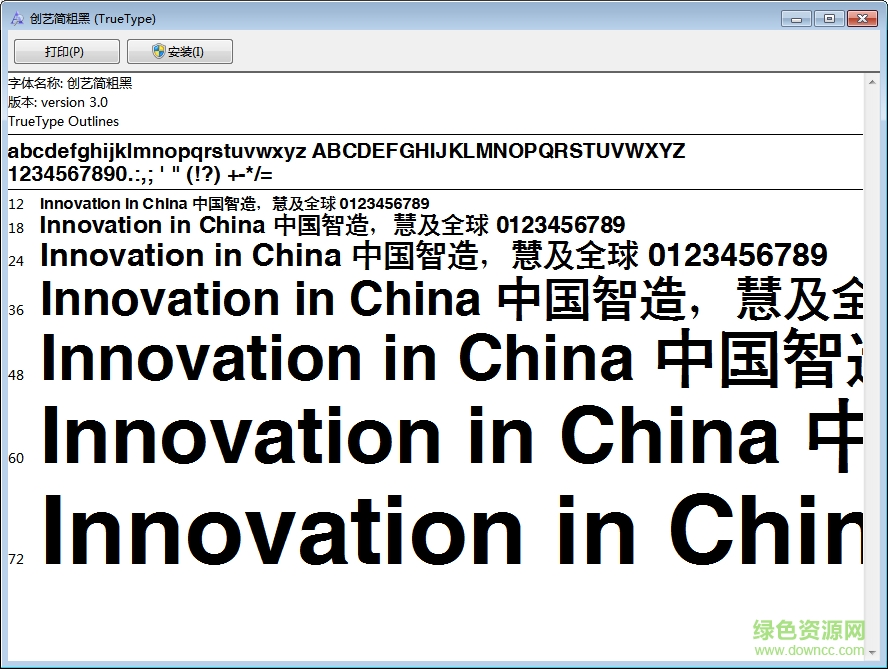
ctcuheisj
ctcuheisj 创艺简粗黑字体是一款线条粗壮的黑体字体,笔画整洁,字形饱满,轮廓清晰,常常用作各种文章的标题或标语,喜欢的朋友快来下载吧!
ctcuheisj字体特点
本款字体端正,大气、壁画横平竖直,笔迹全部一样粗细,整体效果十分不错,适用于文字排版、印刷等方面
ctcuheisj 创艺简粗黑